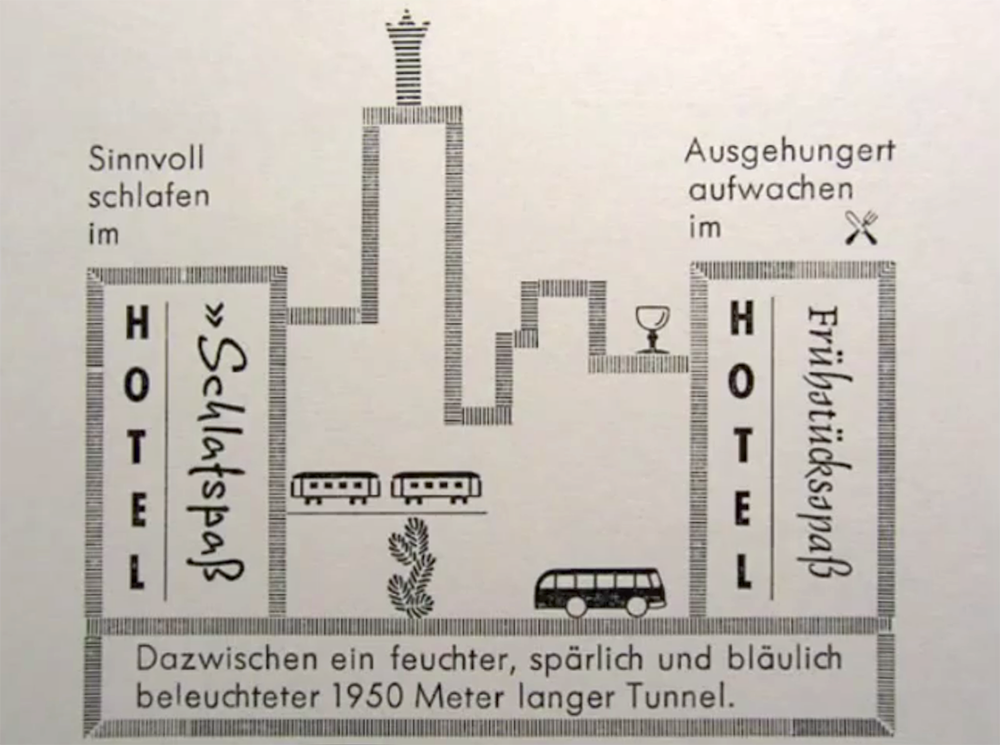
Ein Einblick in etwas komplizierteren Bleisatz
Die Bilder in diesem Filmschnipsel zeigen nicht die gesamte Buchseite. Unter dem Bauwerk gibt es noch einen Text. Das Büchlein soll im November 2012 erscheinen. Der Inhalt komplett im Bleisatz, mit eigenem Handsatz in zahlreichen Schriften, mit Monotype-Satz aus dem Museum der Arbeit in Hamburg und mit Linotype-Satz von einem Kollegen aus Niederkassel.
Diesen Teil der Buchseite herzustellen, hat einige Stunden gedauert. Neben den Schriften Kompliment, Delphin und Futura wurden schraffierte Linien verwendet sowie Blindmaterial, die kleinsten Teile aus hauchdünnem Neusilber, ein Viertelpunkt stark, also 0,094 mm. Man braucht Pinzette, Ahle und eine ruhige Hand, und man muß die ganze Zeit ziemlich schnell Kopfrechnen. Für mich ist es ein Spielplatz, eines der größten Vergnügen in der Werkstatt. Nach dem Druck der Auflage (2200 Exemplare) wird der ganze Spaß wieder abgelegt.
Ein schönes Handwerk :-) Schade, dass das Ergebnis in meinen Augen etwas … sagen wir »zufällig« aussieht.
Was ist denn das für eine witzige Schrift im Vor-und Abspann?
Irgend eine Klamottenschrift aus dem Videoprogramm. Sie heißt Duality, und das Programm hat sie mit einer Kontur versehen. Daß Programme solche Schnapsideen haben, fällt mir immer gar nicht ein. Sie erinnerte mich an die Schrift der Woody-Allen-Filme.
Als Bahnfan, dem dort der Zug ins Auge sticht, frage ich mich natürlich, was da mit den zwei Hotels gemeint ist, schlafen gehen im einen, aufwachen im anderen. Für einen Schlafwagenzug ist die Fahrtstrecke mit knapp 2 km ja etwas arg kurz ;-)
Typographisch interessant dagegen sticht mir gerade der Frühſtücksſpaß ins Auge:
Zwei s-Formen, der Orthographie von langem und runden s folgend, aber das eine eben nicht in der dafür zu erwartenden Langform ... Erzähl mehr dazu! ;-)
Unter dieser Abbildung gibt es einen Text. Das heißt der Text beginnt in seiner Bildumsetzung und wird unten, nicht im Bild, weitergeführt. Der Inhalt erschließt sich erst aus dem fertigen Büchlein, ich kann aus rechtlichen Gründen keine vollständigen Texte abbilden.
Die Delphin hat einige Buchstaben in zwei Formen: g, d und s. Ob es für deren Einsatz Regeln gegeben hat, weiß ich nicht. Ich weiß auch nicht, wie ich das ermitteln kann. Hier scheint der Setzer auf sich gestellt. Ich überlege immer wieder, ob und wie ich die Alternativen einsetze.
So hübsch das auch sein mag ... ich frag mich bei solchen "Bildchenbauereien" im Bleisatz immer, wo die Grenze zwischen ernsthafter Buchgestaltung und angekitschtem Kunstgewerbe verlaufen. In dem Beispiel empfinde ich beispielsweise die eingesetzten Klischees als zuviel des Guten, was die ganze Seite (in meinen Augen) zu einer infantilen Spielerei macht. Nur die Linienkonstruktion mit den reinen Schriften lasse ich mir ja gefallen, aber mit der Vermengung dieser Bildchen unterschiedlichster Stilrichtungen erinnert mich das sehr an schlechte "Computergrafik" mit eingesetzten Clipartgrafiken, die auch nicht zusammen passen.
Versteht mich nicht falsch - das soll keine vernichtende Kritik sein, sondern ist eine eher grundsätzliche Frage, die mich seit schon recht langer Zeit beschäftigt. Wenn man das so am Computer gemacht hätte, würde es m. E. als Buchgestaltung durchfallen. Ist es dann aber gute oder zumindest bessere Buchgestaltung, nur weil es in Blei gemacht wurde?
Ich bin in dieser Frage sehr unentschlossen, weil ich selber gelegentlich in ähnliche Bleibasteleien verfalle - es macht ja auch Spaß. Mittlerweile glaube ich aber, daß Bleisatz bei der Verwendung von alten Klischees, Schmuck, Dekor- und sonstigen Elementen einen höheren Abstraktionsgrad braucht, um nicht kunstgewerblich, infantil oder unbeholfen zu wirken. Vor allem wenn man an Betrachter und Leser denkt, die die technischen Grenzen von Bleisatz nicht einschätzen und demzufolge solche Basteleien eigentlich nicht wertschätzen können.
Oder täusche ich mich da und dieser unbeholfene Reiz ist nun gerade das Tolle ...? Könnte ja auch sein. Andererseits finde ich (und das als passionierter Bleisetzer!), daß Bleisatz "alleene" noch gar keinen Wert hat. Um als "bibliophil" durchzugehen, muss zumindest noch ne Idee dahinterstecken, die dem Ganzen einen Sinn gibt. Aber ich fange an abzuschweifen ...
So hübsch das auch sein mag ... ich frag mich bei solchen "Bildchenbauereien" im Bleisatz immer, wo die Grenze zwischen ernsthafter Buchgestaltung und angekitschtem Kunstgewerbe verlaufen. …
Es geht mir ähnlich, drum auch mein Beitrag weiter oben.
Es geht mir hier nur um den technischen Einblick. Buchseiten würde ich kaum an Fotos von Ausschnitten beurteilen wollen. Ich glaube nicht, daß man das kann. In den Bildern hier ist die ganze Buchseite nicht zu sehen, geschweige die Doppelseite. Diese Seite zeigt weder einen vollständigen Text noch einen vollständigen Entwurf einer Buchseite.
Die Bücher von Max Goldt, die ich setze und drucke, sind jeweils als Gesamtwerk zu sehen. Die Texte werden ausgesucht, in eine sinnvolle Reihenfolge gebracht und mit den Mitteln des Setzkastens ins Bild gesetzt. Zwei der Bücher sind noch im Handel, über die läßt sich reden. Über Fotos von Ausschnitten eher nicht. Das vierte Büchlein wird im Herbst erscheinen.
Diese Diskussion scheint mir auf jeden Fall interessanter als die Definition des Wortes ›Prinzip‹, um schlechten Stil darzustellen. Aber vielleicht sollte man sie von diesem Strang lösen, damit sie nicht immer wieder (wenn auch nur vermeintlich) am Beispiel von Martins Arbeit geführt wird.